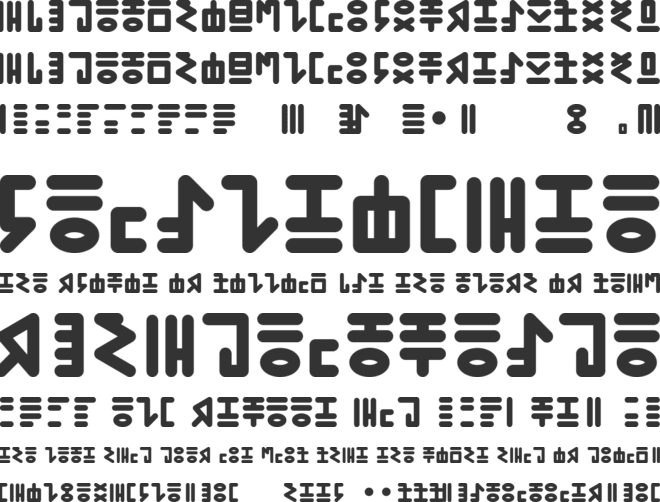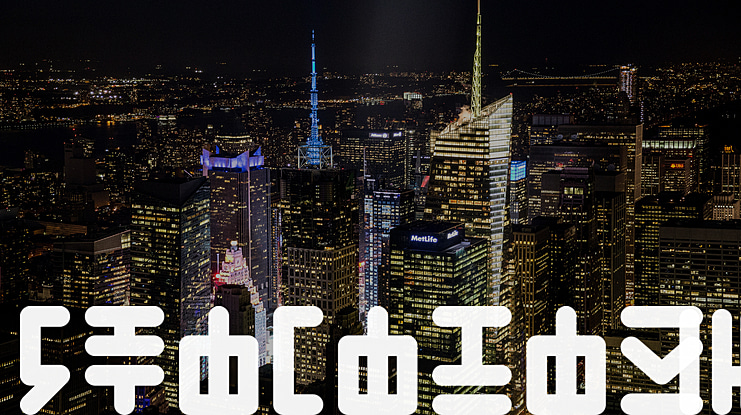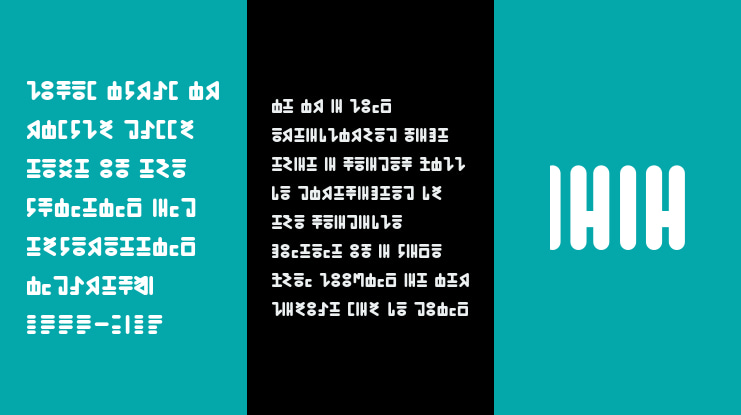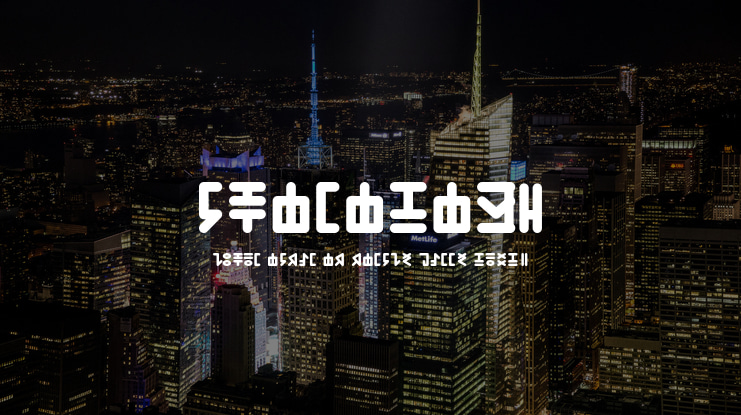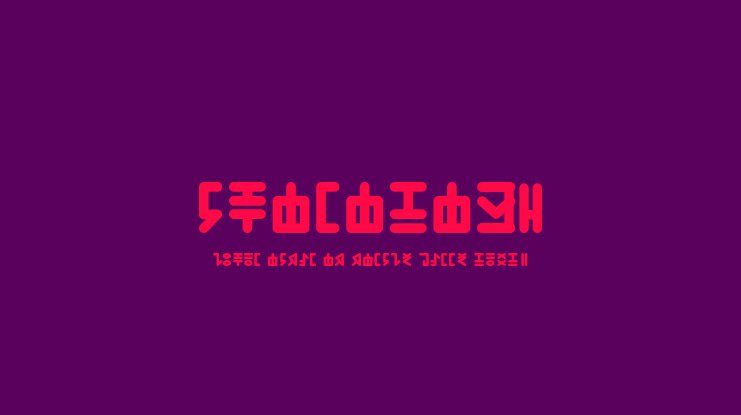
PRIMITIVA Font
Essa fonte é a minha primeira tentativa de criar uma tipografia baseada em Kanji. Não deu muito certo, mas essa aparência de escrita alienígena me agradou bastante. Pretendo criar um dialeto baseado nessa tipografia para uma narrativa de vídeo. Sinta-se a vontade para usá-la como desejar. -> Procure-a como PRIMITIVA no seu sistema.
This font is my first attempt do create a typeface based on kanji. It didn't work the way I wanted, but this aspect of alien script kinda fits well for another purposes. I'll work on a dialect based on this typeface for a narrative I want to record on video. Feel free to use it as you please. -> Search it as PRIMITIVA on your system.